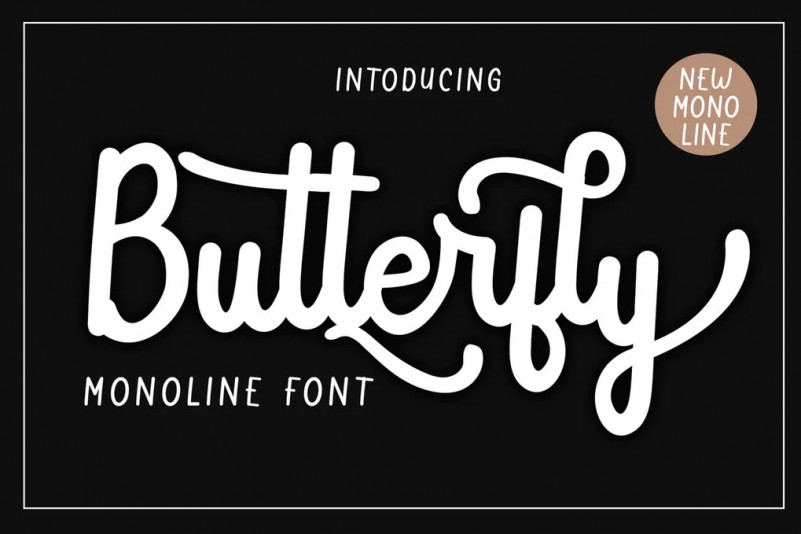
Butterfly Font
Butterfly est une police de type monoline combinée avec un script pour qu’il soit élégant, il y a des fonctionnalités OpenType dedans, adapté pour soutenir une variété de designs et votre entreprise